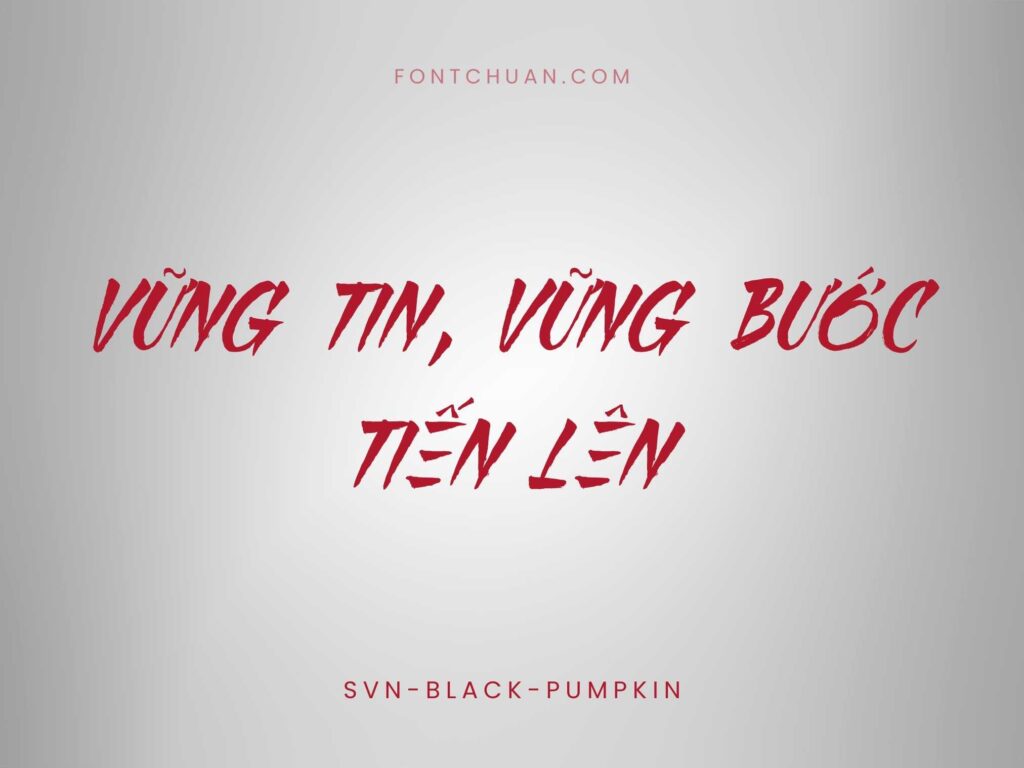
Font SVN Black Pumpkin Việt Hóa
Black Pumpkin là một Font chữ Halloween độc đáo, mang phong cách vui nhộn và thân thiện, phù hợp cho các thiết kế sáng tạo như thiệp mời, tiêu đề, áo thun và các dự án khác. Với cảm giác vui tươi nhưng vẫn gợi lên không khí lễ hội đặc trưng của Halloween, phông chữ này giúp các ấn phẩm trở nên nổi bật và thu hút hơn. Font đã được Việt hóa để hỗ trợ tiếng Việt bởi Styleno.1 Fonts, đồng thời hỗ trợ nhiều ngôn ngữ khác, giúp mở rộng phạm vi sử dụng trên toàn cầu. Font này được thành viên của Font Chuẩn sưu tầm và chia sẻ, đáp ứng nhu cầu của bạn đọc và ứng dụng thực tế vào các dự án thiết kế.
Đặc điểm thiết kế của Black Pumpkin bao gồm các đường nét mềm mại, tạo cảm giác vui tươi và thân thiện. Font này phù hợp cho các ứng dụng như thiết kế thiệp mời, tiêu đề, áo thun và các sản phẩm quảng cáo. Các ngành nghề phù hợp bao gồm quảng cáo, sự kiện, giáo dục và nghệ thuật.